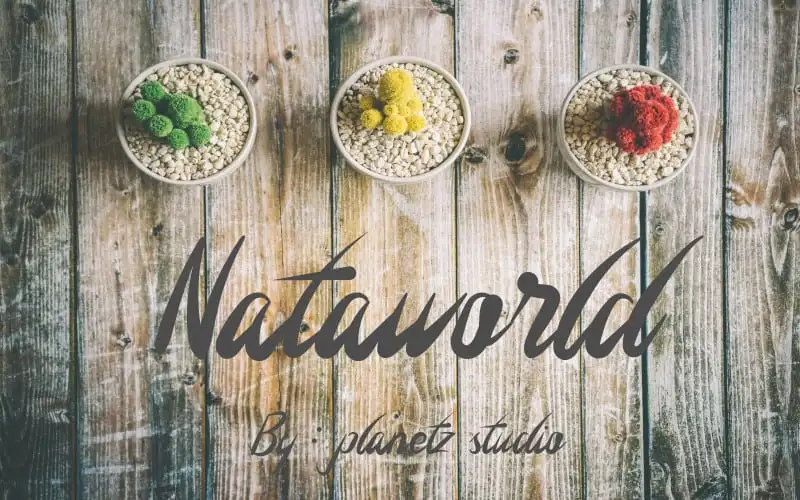
Nataworld Handwritten Font – Download Grátis
A Nataworld Handwritten Font é uma elegante tipografia feita à mão, perfeitamente projetada para se tornar um verdadeiro favorito. Com seu estilo versátil, ela é ideal para criar cartões de convidados únicos e românticos para festas de casamento, artesanato de papel incrivelmente belo, postagens sociais chamativas e muito mais. Adote a Nataworld Handwritten Font em sua próxima criação gráfica e inspire-se com seu formato autêntico e fluido que se adapta à um vasta gama de usos. Experimente agora e faça sua arte digital se destacar ainda mais!